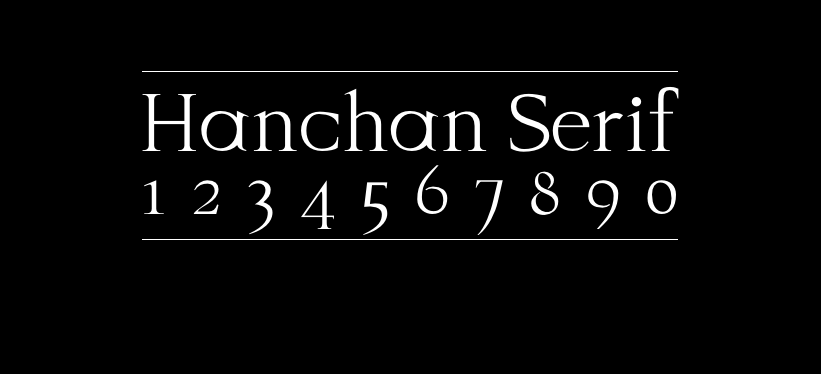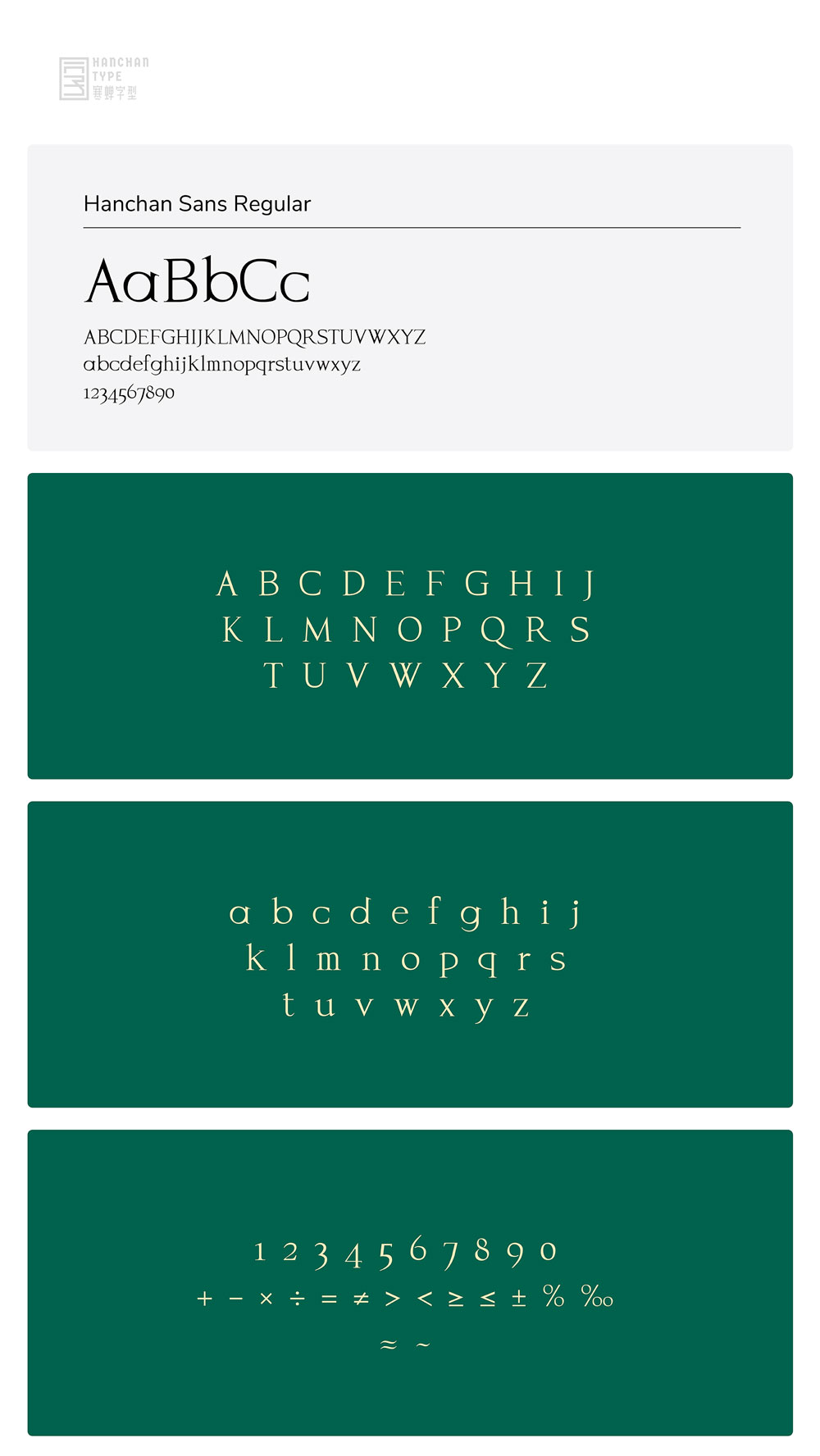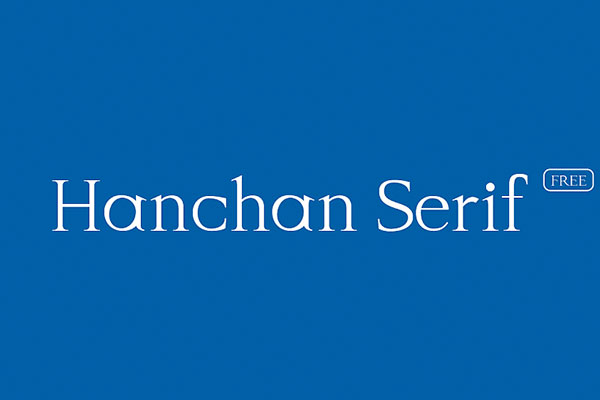
Hanchan Serif
Hanchan Serif字体介绍
Hanchan Serif是中国深圳的平面设计师萧熠Siue创作的衬线英文字体,该字体是寒蝉字型中的其中一款。本站已发布另一款Hanchan Sans,喜欢的可以看看Hanchan Serif的字型优雅帅气,首发于站酷,作者声明免费商用。
Hanchan Serif字体应用示例